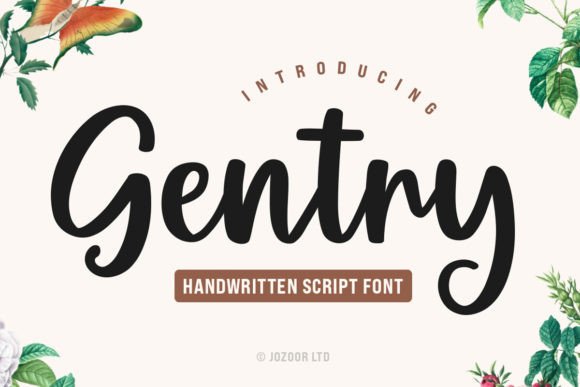
Gentry
適切なデザイン要素を見つけるのは難しい場合がありますが、Gentryは作品を即座に引き立てる優れたコレクションを提供します。
精密に作られたGentryは、クリーンなベクター、滑らかなタイポグラフィ、そして安心のための商用ライセンスを提供します。
POD(オンデマンド印刷)製品、結婚式の招待状、またはソーシャルメディアのグラフィックを作成している場合でも、Gentryは理想的です。